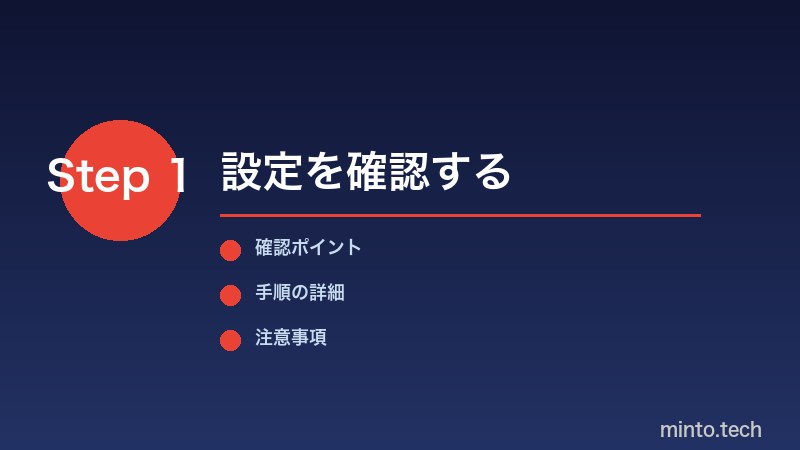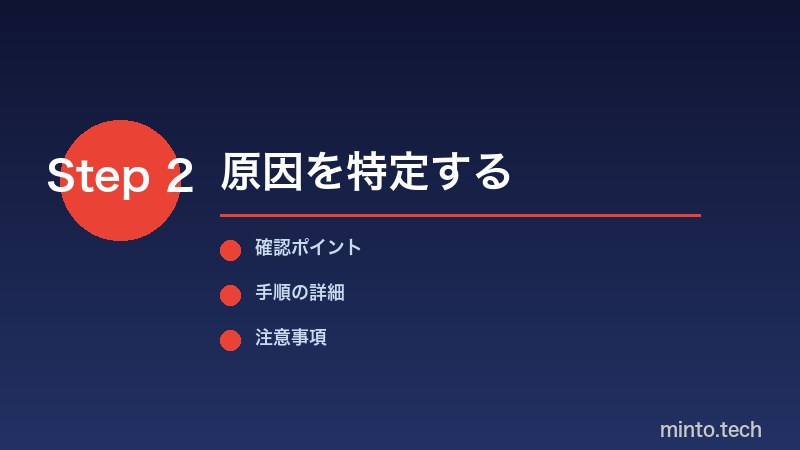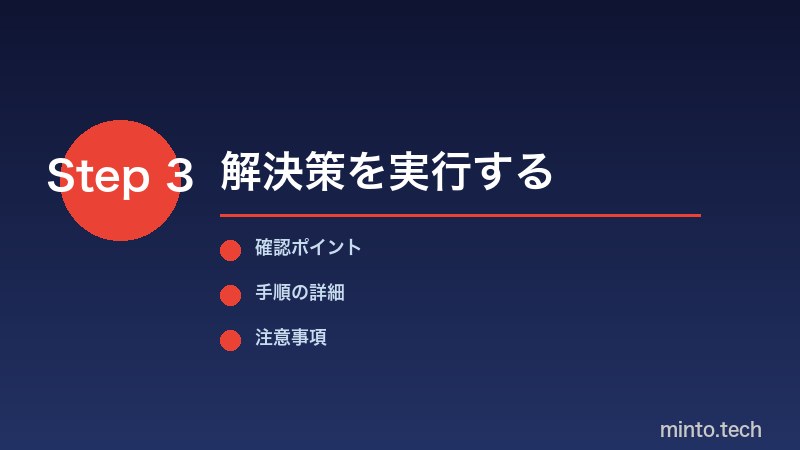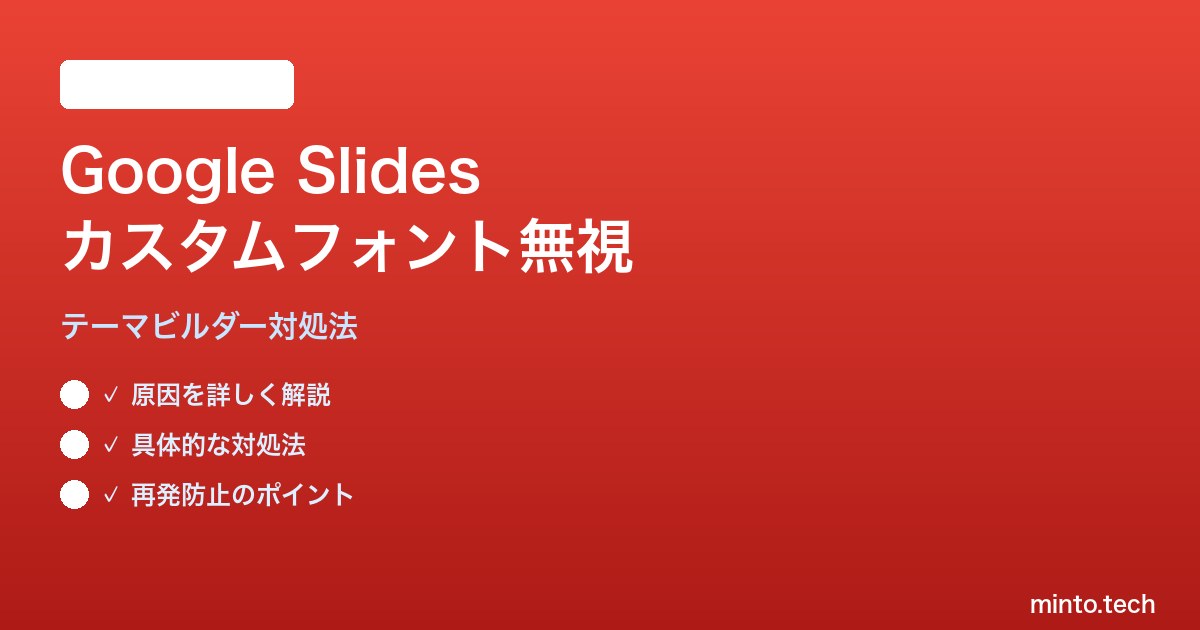
【2026年最新版】Google Slidesテーマビルダーでカスタムフォントが無視される対処法【完全ガイド】
Google Slidesのテーマビルダーでカスタムフォントが無視される原因と解決策
Google Slidesのテーマビルダーでスライドマスターにカスタムフォントを設定したのに、実際のスライドに反映されない――そんな経験はありませんか?特に組織で統一されたブランドフォントを使いたい場合、この問題は業務効率を大きく損なします。本記事では、スライドマスター上書きの仕組みを徹底的に解説し、カスタムフォントが無視される原因を一つひとつ特定して、確実に解消するための方法をお伝えします。
マスタースライドでフォント指定
この記事でわかること
• Google Slidesのテーマビルダー(スライドマスター)とフォント設定の基礎
• カスタムフォントが無視される主な原因とその特定方法
• スライドマスターの上書き設定を正しく適用する手順
• 個別スライドの直接フォント指定との競合を解消する方法
• 組織・チームで統一フォントを運用するベストプラクティス
Google Slidesのテーマビルダーとスライドマスターの基礎
Google Slidesには「テーマビルダー」と呼ばれるスライドマスター編集機能があります。これはMicrosoft PowerPointの「スライドマスター」に相当するもので、プレゼンテーション全体のデザイン・フォント・カラースキームを一括管理できる強力なツールです。
テーマビルダーの階層構造
Google Slidesのテーマビルダーは以下のような階層を持っています。
階層 役割 優先順位
スライドマスター(最上位) 全レイアウト共通のフォント・カラー設定 低(個別設定に上書きされる)
スライドレイアウト マスターを継承しつつレイアウト固有設定 中
個別スライド 直接設定されたフォント・スタイル 高(マスターを上書き)
ここで重要なのは、個別スライドに直接適用されたフォント設定は、マスター設定を上書きするという点です。この仕組みを理解しないまま運用すると、マスターを編集しても変化が見られない状態が続きます。
カスタムフォントとGoogleフォントの違い
Google Slidesで利用できるフォントには以下の種類があります。
フォント種別 追加方法 テーマビルダーでの設定可否
Googleフォント(標準) フォントメニューから選択 可能
カスタムフォント(ウェブフォント) 「その他のフォント」から追加 制限あり
ローカルインストールフォント OSにインストール後フォントメニューから クラウド環境では非対応
特にローカルにインストールしたフォント(企業独自フォントなど)は、クラウドベースのGoogle Slidesでは利用できません。これが「カスタムフォントが反映されない」最大の原因のひとつです。
カスタムフォントが無視される主な原因
フォント追加と同期手順
原因1: 個別スライドへの直接フォント指定が残っている
もっとも多い原因が、個別スライドのテキストボックスに直接フォントが指定されているケースです。Google Slidesでは、スライドマスターで設定したフォントより、個別スライドで直接設定したフォントが常に優先されます。
確認方法は以下のとおりです。問題のスライドを開き、テキストを選択してフォントメニューを確認します。フォント名が表示されている場合、そのフォントが直接指定されている証拠です。
原因2: テーマビルダー内のレイアウト設定が個別に上書きされている
テーマビルダーでスライドマスター(最上位)を編集しても、各スライドレイアウトで個別にフォントが指定されている場合は、マスターの設定が反映されません。スライドマスター編集時は、マスター本体だけでなく、すべてのスライドレイアウトも確認・編集する必要があります。
原因3: 「テーマのフォント」設定が更新されていない
Google Slidesのテーマには「テーマのフォント」という独立した設定があります。テキストボックスのフォントを変更しても、テーマ全体のフォント設定が古いままだと、新規スライドや新規テキストボックスには古いフォントが適用され続けます。
原因4: フォント自体がGoogle Slidesで未対応
企業独自のOTF/TTFフォントや、OSにローカルインストールされているフォントはGoogle Slidesでは使用できません。そのため、設定してもフォールバックフォント(Arialなど)に自動置換されます。
原因5: 旧バージョンのテーマが残存している
既存のプレゼンテーションにテーマを適用・変更した場合、古いテーマのスタイルが個別スライドに「べた書き」で残るケースがあります。この場合、新テーマのフォント設定は適用されません。
カスタムフォントを正しく反映させる対処法
対処法1: スライドマスターとすべてのレイアウトのフォントを統一する
テーマビルダーを開き、スライドマスター(左側パネルの最上位のサムネイル)を選択します。次に、すべてのテキストプレースホルダーを選択(Ctrl+A)し、フォントを設定します。
さらに、スライドマスターの下に表示されるすべてのレイアウト(タイトルスライド、コンテンツ、空白など)に対して同じ操作を繰り返します。どれかひとつでも設定が漏れると、そのレイアウトを使用したスライドには古いフォントが表示されます。
1. 「表示」メニューから「テーマビルダー」を選択
2. 左側パネルの最上位のスライドマスターをクリック
3. 全テキストプレースホルダーを選択してフォントを変更
4. 各レイアウトにも同様にフォントを設定
5. テーマビルダーを閉じる
対処法2: 個別スライドのフォント直接指定をリセットする
既存スライドに直接フォントが指定されている場合、そのスライドを選択し「スライド」メニューから「テーマを適用」を選ぶことで、マスターの設定をリセットできます。ただし、この操作でスライド固有のカスタム書式設定が失われる可能性があります。作業前にバックアップとしてコピーを作成しておくことを推奨します。
対処法3: テキストを「書式なしでペースト」して再適用する
問題のテキストをコピーした後、「Ctrl+Shift+V(または Cmd+Shift+V)」で書式なしペーストを行うと、直接指定されたフォントが除去され、マスターのフォントが適用されます。大量のスライドがある場合は手間がかかりますが、確実に効果があります。
対処法4: Googleフォントを使用してカスタムフォントを近似させる
企業独自フォントなど、Google Slidesで非対応のフォントを使いたい場合は、見た目の近いGoogleフォントで代替するのが現実的な解決策です。
用途 推奨Googleフォント 特徴
見出し(モダン・サンセリフ) Google Sans / Montserrat クリーンで視認性が高い
本文(読みやすさ重視) Noto Sans JP / Roboto 日本語対応・長文に最適
タイトル(インパクト重視) Oswald / Raleway プレゼンの印象を引き締める
コード・技術系資料 Source Code Pro 等幅フォントで視認性良好
対処法5: Google Apps Script(GAS)でフォントを一括置換する
スライドが多数ある場合や、定期的にフォントを統一する必要がある場合は、Google Apps Scriptを利用した自動化が有効です。スクリプトエディタから以下の手順で一括置換が可能です。
1. Google Slidesを開き、「拡張機能」→「Apps Script」を選択
2. スクリプトエディタに処理を記述
3. 対象フォント名を旧フォント名から新フォント名に置換する関数を作成
4. スクリプトを実行してフォントを一括変更
この方法は、数十枚以上のスライドで効果を発揮します。ただし、スクリプト実行には「Google Drive」へのアクセス権限が必要です。
対処法6: 新規プレゼンテーションにコンテンツを移行する
旧テーマの残存が原因でどうしても解消できない場合、新規プレゼンテーションを作成して正しいテーマを設定した後、既存スライドを書式なしで貼り付けて移行する方法が最終手段として有効です。
代替フォントへの置換
テーマビルダー設定のトラブル比較表
問題の症状 主な原因 推奨対処法 難易度
既存スライドだけ反映されない 個別スライドへの直接フォント指定 書式なしペースト / テーマ再適用 低
一部のレイアウトだけ変わらない レイアウト個別の上書き設定 テーマビルダーで全レイアウト編集 中
フォントが別のフォントに変わる フォント非対応(ローカルフォント等) Googleフォントで代替 低
新規スライドは反映されるが旧スライドは変わらない 旧テーマの残存 新規PPTに移行 または GAS一括置換 高
テーマ適用後にフォントが混在する テーマフォント設定の未更新 テーマビルダーでフォント再設定 中
チーム・組織で統一フォントを運用するベストプラクティス
ブランドテーマテンプレートを共有する
組織内でフォントを統一するには、あらかじめ正しいテーマ・フォントが設定されたテンプレートファイルをGoogle Driveで共有し、全員がそこからプレゼンテーションを新規作成するルールを設けることが効果的です。既存ファイルへのテーマ適用は属人的な作業ミスが起きやすいため、「最初から正しいテンプレートで始める」運用が最も堅牢です。
フォント確認チェックリストを作成する
プレゼンテーション提出前に、フォント確認のチェックリストを設けると効果的です。スライドの「ファイル」→「印刷プレビュー」で全スライドを確認し、フォントがずれていないかを目視で確認する習慣をつけましょう。
Googleフォントを「固定リスト」で管理する
チーム内で使用するGoogleフォントを2〜3種類に絞り込み、「見出しはNoto Sans JP Bold、本文はNoto Sans JP Regular」のような内部ガイドラインを文書化しておきます。誰でも同じ設定を再現できるため、フォントの混在を防ぐことができます。
• テーマビルダーではスライドマスター本体だけでなく、すべてのレイアウトにもフォントを設定する
• 既存スライドには「テーマを再適用」または「書式なしペースト」でフォント直接指定を解除する
• ローカルフォントや独自フォントはGoogle Slidesでは使用できないため、Googleフォントで代替する
• 大量のスライドを一括変更したい場合はGoogle Apps Scriptを活用する
• チームでの統一運用には、正しいテーマが設定されたテンプレートファイルを共有する仕組みを作る
フォントの統一はプレゼンテーションの品質と信頼性を高める重要な要素です。今回紹介した手順を参考に、Google Slidesのテーマビルダーを最大限に活用してください。